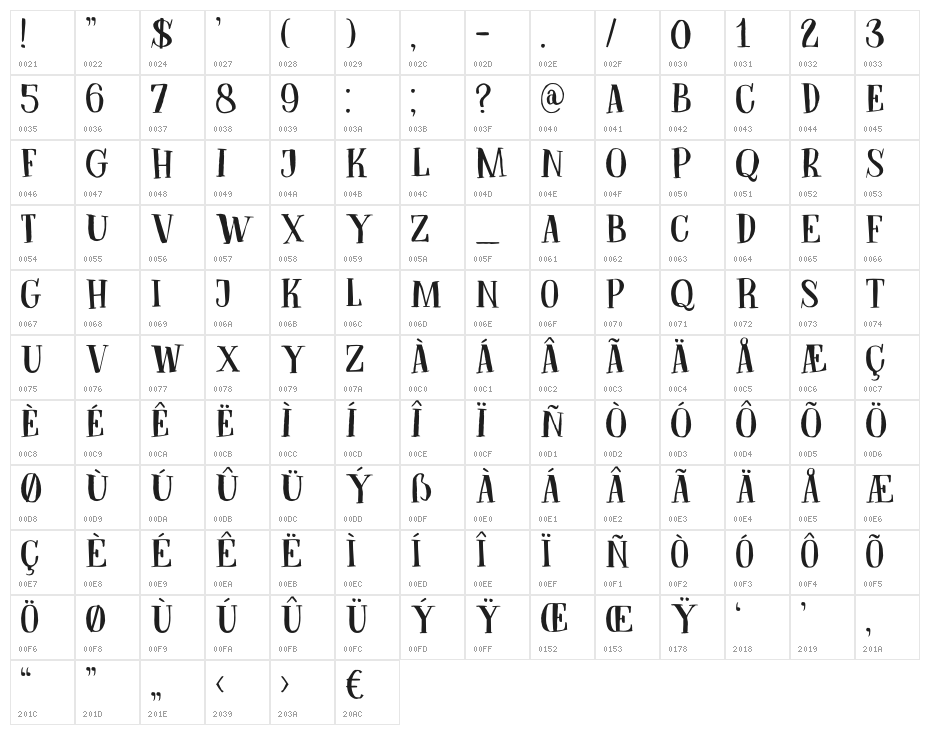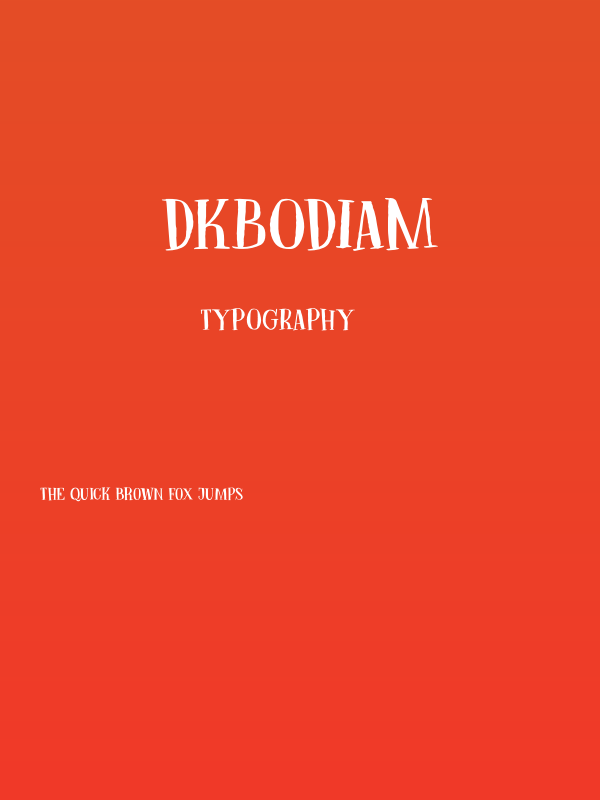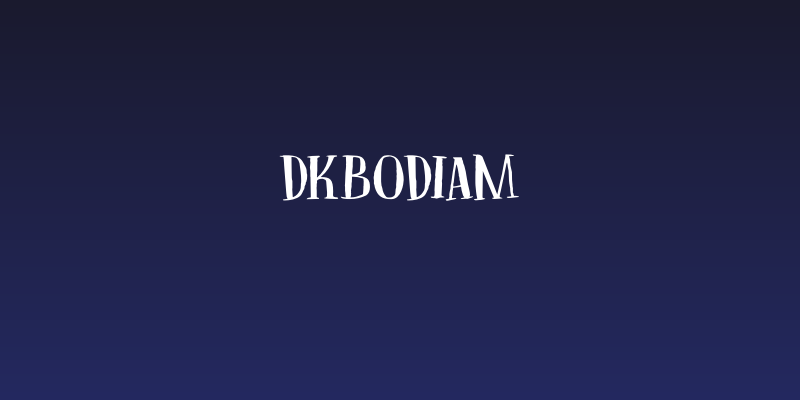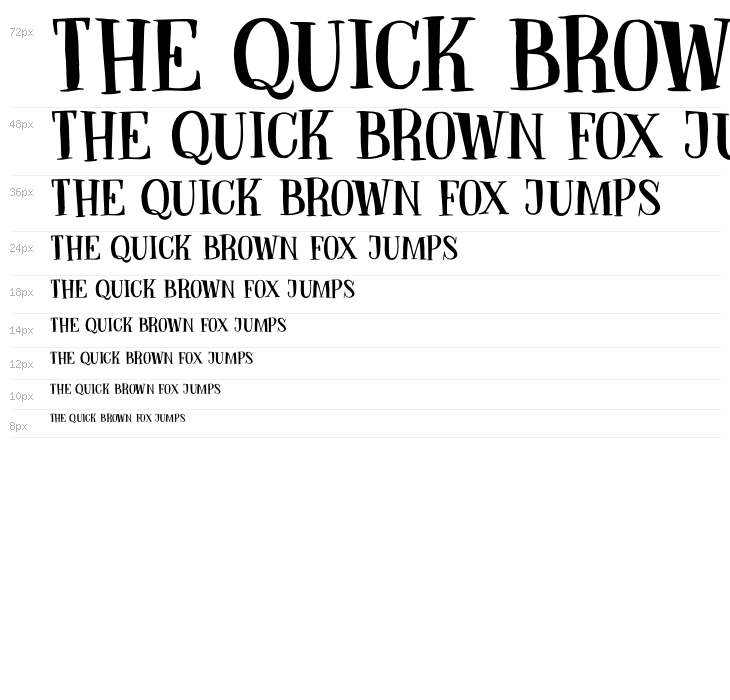
DKBodiam Font
| Gesamtstil | Playful, Hand-drawn |
| Vorgeschlagene Projekte | Ideal for children's books, playful branding, creative posters, and any project needing a fun, engaging look. |